CHE RUOLO HANNO I FONT NEL PACKAGING?
Non si tratta solo delle scritte in piccolo! Loghi, immagini, forme e colori sulle confezioni attirano la maggior parte dell'attenzione, sono riconosciuti, suscitano emozioni.
Nonostante l’importante impatto visivo, il tipo di scrittura a volte passa in secondo piano nel design del packaging; eppure non solo assume compiti importanti, ma è addirittura parte integrante del design.
La giusta tipografia per un pacchetto non riguarda quindi solo il modo in cui tutte le informazioni importanti e richieste possono essere inserite nello spazio disponibile. Si tratta di scoprire che effetti hanno i diversi font, cosa dicono di te e del tuo marchio, quanto bene si adattano e come meglio si inseriscono nella composizione generale.
Ti spieghiamo di seguito le caratteristiche di base a cui dovresti prestare attenzione.
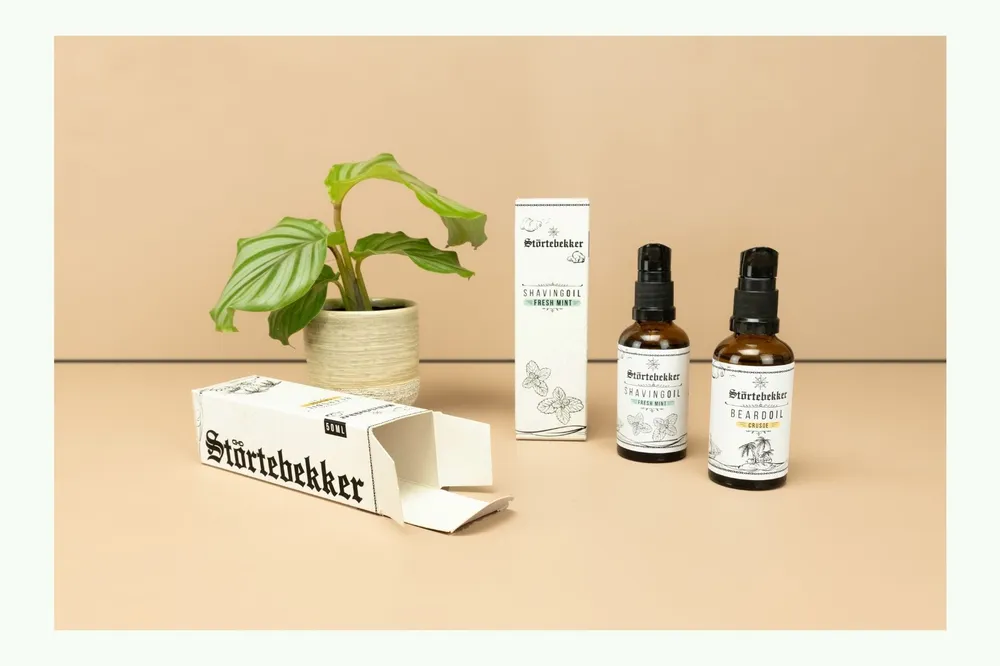
EFFETTI DEI FONT
I font raccontano storie, ma non lo fanno solo formando parole. Oltre all’aspetto informativo di cui abbiamo bisogno per la comunicazione e la comprensione nella vita quotidiana, i caratteri hanno anche una grande influenza su di noi. La tipografia si occupa quindi di come i caratteri e il loro design ci influenzano.
Questo perché ogni carattere ha il suo proprio carattere, che è già insito nella forma di base delle lettere (i tipografi parlano, in questo contesto, di architettura di un carattere). Questo significa che caratteri diversi ottengono effetti diversi:
I caratteri che si basano sulla scrittura a mano e hanno forme aperte e rotonde sono percepiti come amichevoli e caldi.
I caratteri geometrici e chiusi hanno le associazioni opposte e appaiono tecnici e freddi.
Le lettere larghe trasmettono stabilità, mentre i caratteri stretti creano un'impressione di instabilità. Analogamente, gli angoli retti possono essere percepiti come duri e quelli arrotondati come morbidi.
Inoltre, gli elementi del carattere come gli ascendenti e i discendenti fanno una notevole differenza, così come l'enfasi sull'orizzontale o sul verticale:Gli ascendenti e i discendenti corti appaiono giù di corda, ma se sono lunghi e pronunciati, diventano un'espressione di eleganza.
Se il focus di un carattere è sull'allineamento orizzontale, appare più dinamico; un focus sulla verticale, invece, lo rende statico.
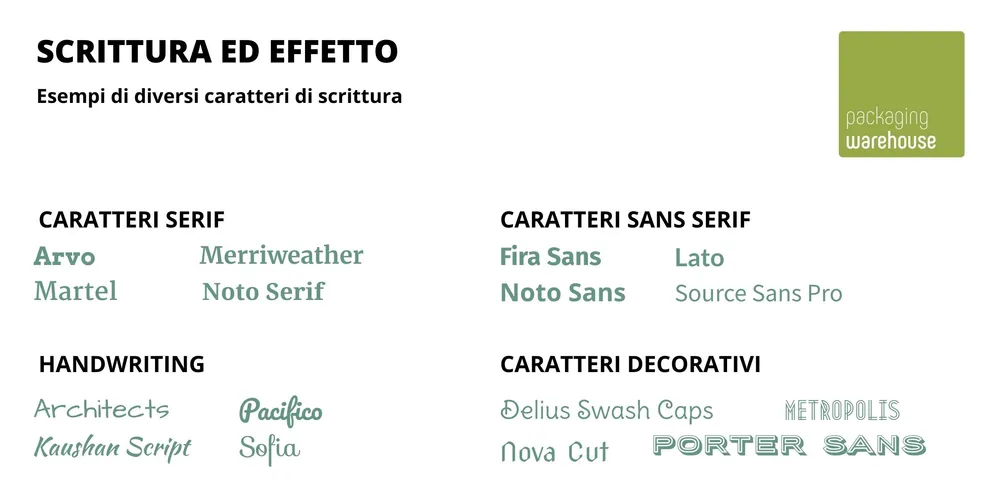
Inoltre, ci sono alcune peculiarità e caratteristiche speciali che sono particolarmente importanti per il corporate design; anche se sono piccoli, possono avere una grande influenza sull'impressione generale. Il design dei caratteri può anche cambiare il significato di una parola o di un intero contenuto, e proprio come le forme e i colori, i caratteri risvegliano certe emozioni e associazioni nei tuoi clienti.
Quando si usano i font come elemento di design, tutto ruota quindi intorno alla domanda: come si possono utilizzare al meglio le proprietà e gli effetti dei diversi font per attrarre i tuoi clienti?
IL CARATTERE TIPOGRAFICO NEL DESIGN DEL PACKAGING - UNA QUESTIONE DI TIPI
Alla domanda di cui sopra si può rispondere solo se si conoscono i tipi di font più importanti e le loro caratteristiche.
Caratteri serif
Questi font sono caratterizzati da una piccola linea alla fine del tratto di una lettera: il serif. Sono dei veri classici e trasmettono anche eleganza. Di conseguenza, il loro effetto è accurato e letterario.
Poiché sono così antichi e comuni, la loro forma è molto familiare ai nostri occhi. Questo rende i font serif facili da leggere. Sono quindi una buona scelta per passaggi di testo più lunghi e stampe piccole.
Rappresentanti ben noti: Times New Roman
Caratteri sans serif
"Sans Serif" significa "senza serif". Facendo a meno dei piedini, questi font appaiono moderni, chiari, businesslike e puliti.
Variando lo spessore, si possono creare impressioni ancora più diverse: i font Sans Serif spessi appaiono forti e mascolini, mentre quelli sottili appaiono nobili e glamour.
Rappresentanti ben noti: Helvetica
Caratteri handwriting
Inconfondibile come la tua stessa scrittura: questa è l'idea alla base dell'handwriting ed è esattamente quello che sembra.
Il risultato è una selezione incredibilmente varia, che va dai font calligrafici ai caratteri che cercano davvero di imitare la scrittura a mano. L'obiettivo primario è quello di creare un carattere individuale e unico - l'aspetto rappresentativo è chiaramente in primo piano qui.
Rappresentanti ben noti: Sacramento
Caratteri decorativi
I caratteri tipografici decorativi trasformano le lettere in vere e proprie opere d'arte. Questo rende il loro impatto emotivo sull'osservatore particolarmente forte, ed è il motivo per cui sono usati principalmente come caratteri tipografici per il logo. Come testo secondario o per il testo continuo, risulterebbero troppo plateali e quindi sprecati.
Questi font spesso riflettono le tendenze attuali, e allo stesso tempo sono usati per modellare il branding di un'azienda per molti anni.